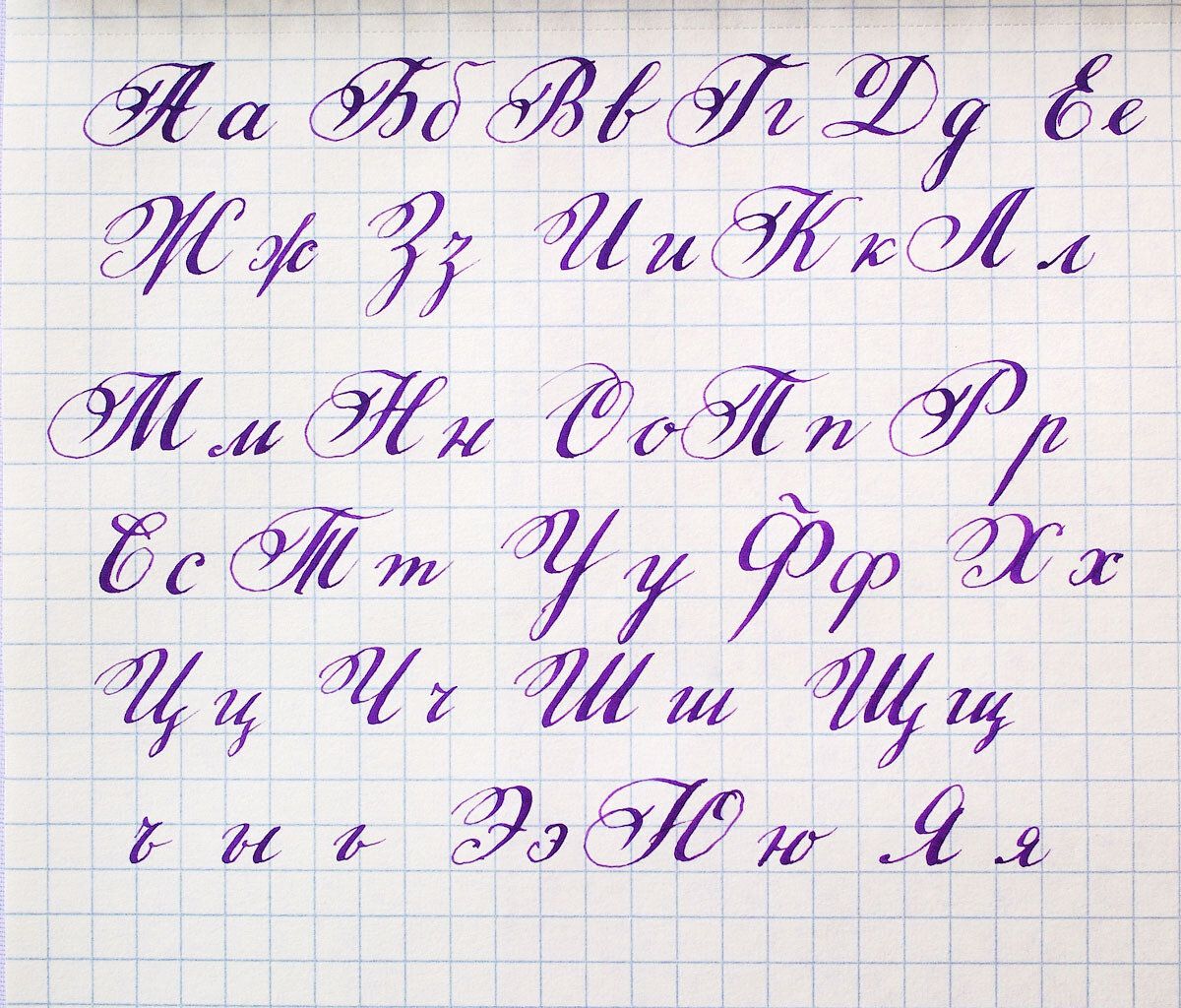
Красивый шрифт для фотошопа русский прописью.
Русские рукописные шрифты. Сделать свой русский рукописный шрифтНа днях наша группа столкнулась с серьезнейшей проблемой — за пропуски пар надо сдать рефераты, написанные от руки. За два пропуска — 1 реферат на 15 листов! Да я за весь семестр столько бумаги не измарал, слава яйцам. Поэтому пришлось пойти на хитрости, а именно: найти нормальные (кириллические) и загнать их в Microsoft Word, и распечатать наши рефераты.
Вот эта подборка из 80-ти русских рукописных шрифтов. В архиве вы найдете следующие (и др.) экземпляры:
Сделать свой русский рукописный шрифт
Но, скачав эти шрифты, стало понятно, что никто не поверит, будто мы пишем, как Пушкин, Боярский или Моцарт. Поэтому пришлось сделать рукописный шрифт самим. Но как сделать свой шрифт, как две капли воды похожий на ваш обычный почерк?
Далее, на чистом листе (в линейку и в клетку не подойдут) пишем все буквы русского (английского, и других при необходимости) алфавита, а также цифры и спец.
Сканируем получившееся творение. Далее режем отсканенную картинку на отдельные буковки и циферки (фотошоп или банально пэйнт подойдет), называем соответственно.
Самая нижняя линия (Win Descent) – максимальный предел для букв с хвостиком (ц,у,щ,з,р,д). Если необходимо, можно ее опустить:
Третья снизу линия (x-Height) – максимальная высота маленьких букв.
Четвертая (CapHeight) – максимальная высота больших букв, цифр, а также буквы «в», и может быть для кого-то «д» и «б».
И пятая снизу линия – линия края верхней строки. (по-моему =)
При составлении и написании любого текста необходимо уделять внимание его оформлению, а именно шрифтам.
Не забывайте о том, что главная цель любого текста — донести до аудитории вашу идею, однако внешний вид также помогает и способствует этому.
Хочу привести вам 15 примеров рукописных шрифтов, которые обрели достаточно широкое распространение, скачать их сегодня можно совершенно бесплатно. Обычно они используются при создании приглашений, грамот и придают любому тексту особую элегантность и изысканность.
BetinaScriptCTT
Ludvig-van-Bethoveen
Carolina
Corinthia
DS-Izmir-Normal
Julia-Script
Parnas-Deco
New-Record
Rondo-Twin-Thin
Scriptorama
Shampanskoe-script
Stradivari-script
Teddy-Bear
Vivaldi-script